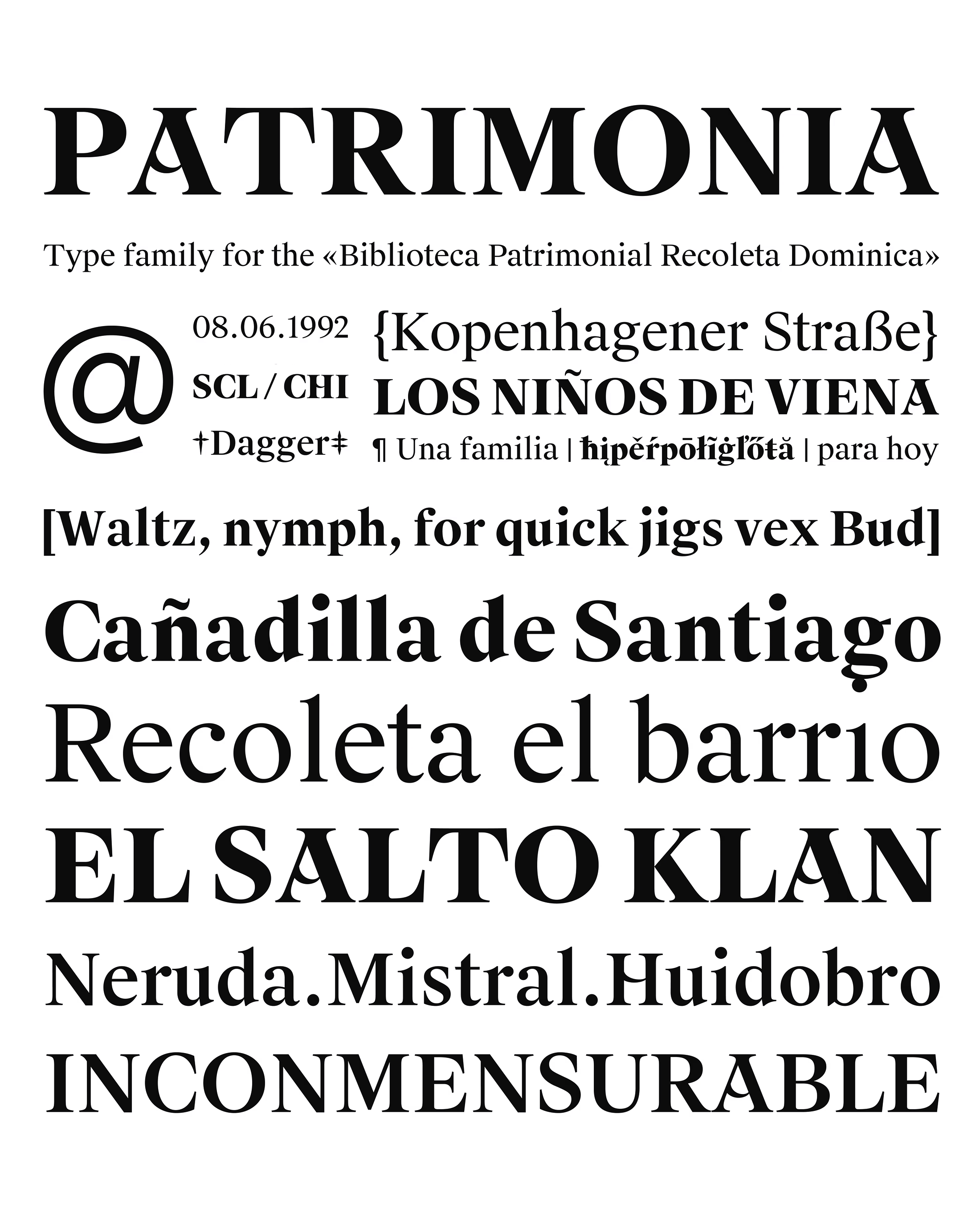
| Descripción | Patrimonia es una tipografía institucional inspirada en los libros antiguos y en colecciones históricas de revistas resguardadas por la Biblioteca Patrimonial Recoleta Dominica y la imprenta nacional. Su carácter emerge del diálogo entre las formas editoriales del pasado y las necesidades contemporáneas de identidad, proponiendo una voz tipográfica sobria y culturalmente anclada para aplicaciones institucionales |
| Clasificación | Texto |
| Familia(s) | Parimonia regular, Patrimonia Mediana, Patrimonia Gruesa, Patrimonia Oscura |
| Estilos | 4 |
| Cliente | Biblioteca Patrimonial Recoleta Dominica |